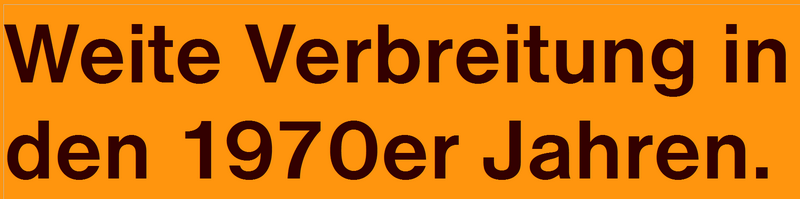
AG-Buch-Schnitt?
Was es mit diesem Schnitt auf sich hat, überlege ich mir schon seit Langem. Er ist von einer Schriftensammlung von Data Becker. Ich habe bemerkt, dass dieser Schnitt ab Anfang der 1990er Jahre nicht mehr zum Einsatz gekommen ist - oder nur noch ganz selten, und dann möglicherweise bei solchen, die bereits die Schrift erworben hatten. Es sieht aus wie ein Schnitt der AG Buch von Günter Gerhard Lange, zwischen Regular und Medium. Ich habe alle AG-Book-Versionen auf myfonts.com durchgesehen, und dort findet sich nur die etwas dickere Medium-Variante, die z. B. von der Lufthansa her bekannt ist.
In der Tat, ich dachte, das wäre der Data-Becker-Name, immerhin sind alle anderen Schriften umbenannt. Aber was ist ihre Geschichte? Bei MyFonts steht URW++ und 2000. Als wäre sie neu eingeführt worden. Sie ist aber ganz offensichtlich schon älter und besitzt eine bemerkenswerte Ähnlichkeit zur AG Buch.
Also Lufthansa ist nicht AG Buch, sondern Helvetica, das ist einfach der Corporate Font der Lufthansa seit Otl Aicher oder gar prä, ich weiss es nicht genau … Die unter »Nimbus« laufenden Schriftschöpfungen sind von URW, und zur Geschichte hat auf typophile ein netter Mensch aus »Robert Norton's wonderful book 'Types Best Remembered/Types Best Forgotten'«, Peter Karows Beitrag zur Helvetica komplett zitiert. Wird einem fast ein bisschen schwindelig beim Lesen, aber beantwortet vielleicht die Frage nach den Ähnlichkeiten. R.I.P. Max Miedinger …
I started the IKARUS program late in 1972. In February 1973 we had completed the digitizing and plotting parts, so we could produce the first typefaces. My first customer was Walter Florenz Brendel from Dusseldorf. He had prepared the master characters for digitizing in a large size. As we do it today: 6 inches for bodysize. It was the typeface Olympia. I asked him whether he drew the characters himself: 'No, my designer did it.' They were inked and black/white. Later we used just pencil drawn contours. Then he added after severe questioning: 'Yes, the typeface is very close to Helvetica of the Stempel AG.' (formerly part of today's Linotype-Hell AG) In 1976, I met with Max Miedinger. He said, 'I am the designer of the famous Helvetica. I did it in 1957. Now, Stempel earns lots of money with it, but I am out of the game. I feel cheated.' In 1977, we digitized the Helvetica originals with IKARUS from large friskettes.... We got that service contract from Stempel AG in Frankfurt. In 1978, we digitized Holsatia, a Helvetica-clone made by the Hell company. In 1980 we digitized SANS for IBM. They never used it. In 1981, we helped the Typoart company in the DDR to digitize their Maxima, another clone of Helvetica. I guess this was the best data we ever made. One font (800 char.) included also Greek and Cyrillic and lots of accented characters. In 1982, we digitzed the Akzidenz Grotesk Buch for the Berthold company; I viewed it as another clone of Helvetica, as did Rene Kerfante, manager of the Stempel AG. In 1983, Hermann Zapf started the design of our typeface URW Grotesk because a very big publishing company (Axel Springer) wanted to have a sans serif alternative typeface. In 1985 we did our Nimbus Sans tyepface, a merger out of Helvetica, AG Buch, Hosatia, and others. We tried to avoid some of the mistakes with the old Helvetica. In 1986/87, the Stempel AG produced the Neue (New) Helvetica. They cloned themselves, but called it a new and innovative design. In 1987, we digitized the Arial typeface for Monotype, another clone. This time, Rene Kerfante, being manager at Monotype convinced me that Arial is very different from Helvetica. In 1990, we delivered new data of Helvetica to Adobe because they could not handle their old data of Helvetica with ATM. They wanted a clean start. In 1992, we made our URW TypeWorks product (500 masters +Inline, Outline, Relief, Shadow and Round). Now, one can have Nimbus Sans as a 'sixpack'. In 1993, Stefan Rogener (a typograph living in Hamburg) made statistics on the use of typefaces in the advertising branch. He came out with: 'By more than 90%, the creatives use Helvetica, Futura, Garamond, and Baskerville. They are stupid. Give me a pistol.' He is still alive. But Max Miedinger died in the late seventies, poor and without glory. I can't forget Helvetica.
Miedinger hat übrigens auch die "Swiss" entworfen, die als Helvetica-Klon den Corel-Paketen beilag.
Danke für den Link, ich werde den Artikel bei Gelegenheit lesen. Warum soll Lufthansa Helvetica sein, der von mir gezeigte Schnitt ist ganz klar Teil von AG Buch? Da bin ich mir 100% sicher, dass der Schnitt der vom Lufthansa-Schriftzug ist. Oder wird das im Artikel beantwortet? Dann verzeiht mir...
… Warum soll Lufthansa Helvetica sein, der von mir gezeigte Schnitt ist ganz klar Teil von AG Buch? Da bin ich mir 100% sicher, dass der Schnitt der vom Lufthansa-Schriftzug ist. …
Weil die Lufthansa nun mal die "DLH Helvetica" einsetzt.
Warum soll Lufthansa Helvetica sein, der von mir gezeigte Schnitt ist ganz klar Teil von AG Buch?
Und falls Zweifel bestehen, ob das Logo nicht doch aus einer anderen Schrift ist, schau mal hier:
Interessant ist auch die 1962 an die HfG Ulm in Auftrag gegebene „Studie 1400/0 – Erscheinungsbild der Lufthansa“, die als Grundlage für die Erstellung eines neuen Erscheinungsbildes diente und die auszugsweise im Buch abgedruckt ist. Daraus heißt es. „Das Wortzeichen ‘Lufthansa’ sollte aus einer firmenspezifischen Gebrauchsschrift gesetzt werden. Die Gepflogenheit, Wortzeichen in einer einmaligen, eigenen Form zu verwenden, geht zurück“. Auch wenn diese Einschätzung Otl Aichers auf die damalige Zeit zutreffen mochte, …
Ein Freund, der seit Jahr und Tag bei der Lufthansa im CD-Bereich arbeitet, hat mir auch mal das Otl-Aicher-Manual im Büro zwischen Autobahn und Werksflughafen  zum Blättern gegeben, aber ich bin leider kein Eidetiker, sonst würd ich es ja drauf schwören  :nicken:
Aber noch mal zurück zur Geschichte – die Helvetica hat ja den Top-Slot bei Jürgen Siebert's »hundert besten Schriften« inne, und da findet sich auch einiges Interessantes zur Entstehung: http://www.100besteschriften.de/1_Helvetica.html#a1.
Luc Devroye zitiert Nick Shinn aus einer Diskussion bei typophile in seinem Eintrag über Max Miedinger, der dort auch mit folgendem aufwartet (Here is a document showing the working process of plagiarizing Akzidenz Grotesk that Miedinger oversaw.) Arrgh …
Das Typedesigner als Reaktion auf die Helvetica Omnipräsenz noch mal einen Schritt zurück gegangen sind um quasi Prä-Miedinger-Varianten zu erzeugen (Bruno Maag, Christian Schwartz’ FF Bau: noch mehr Geschichte hier: http://www.fontblog.de/C420185419/E430231085/index.html), ist wohl als Reaktion auf das Dilemma zu verstehen, den der Erfolg der Helvetica erzeugt hat (Nick Shinn meint, er hat nichts gegen die Schrift an sich, nennt aber die Allgegenwart »einen Affront gegen mich selbst und andere Schriftgestalter heutzutage« weil sie als »voreingestellte System-Ästhetik« fungiert, und den Sinn von Schriftgestaltung als einen sozio-ökonomischen, kulturellen Faktor in Frage stellt. Naja, als rotes Tuch ist die gute alte Helvetica denn auch von »ihren« Klonen abgelöst worden, siehe auch Sebastian Nagels Signatur:
* Berthold hat ja immer gepocht auf deren extrem hohen Qualitätsstandards für die Reinzeichnungen deren Schriften. Eventuelle Differenzen zwischen AG Buch und Helvetica sind demnach auf von Berthold durchgeführte Verbesserungen zurückzuführen :–)
** gemeint ist die Breite Grotesk der Leipziger Schriftgießerei Schelter & Giesecke